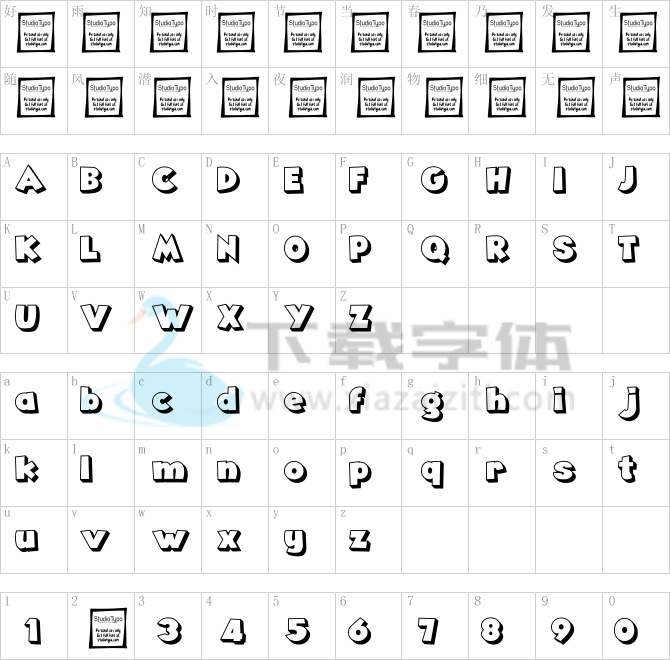
Angella Outline.otf字体下载,这款字体结构工整、笔画清晰,兼顾美观与易读性,适用于标题、正文、海报、包装、LOGO 等多种场景。字形优雅稳定,风格百搭耐看,适配日常排版与创意设计,让文字呈现更舒适、更具质感。Angella Outline.otf字体下载一笔一画,皆是细节,以均衡的比例、流畅的线条打造舒适视觉体验,字形端正大气,风格简约现代。无论是商业设计、品牌宣传还是日常排版,都能轻松驾驭,让文字更有格调与力量。Angella Outline.otf字体下载字体下载。